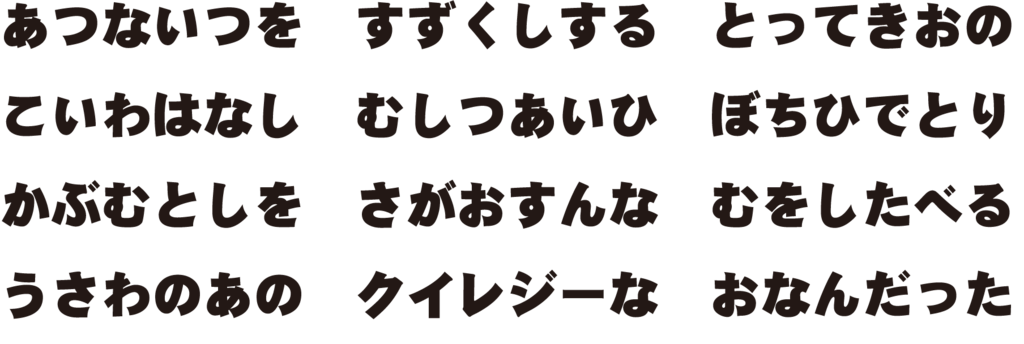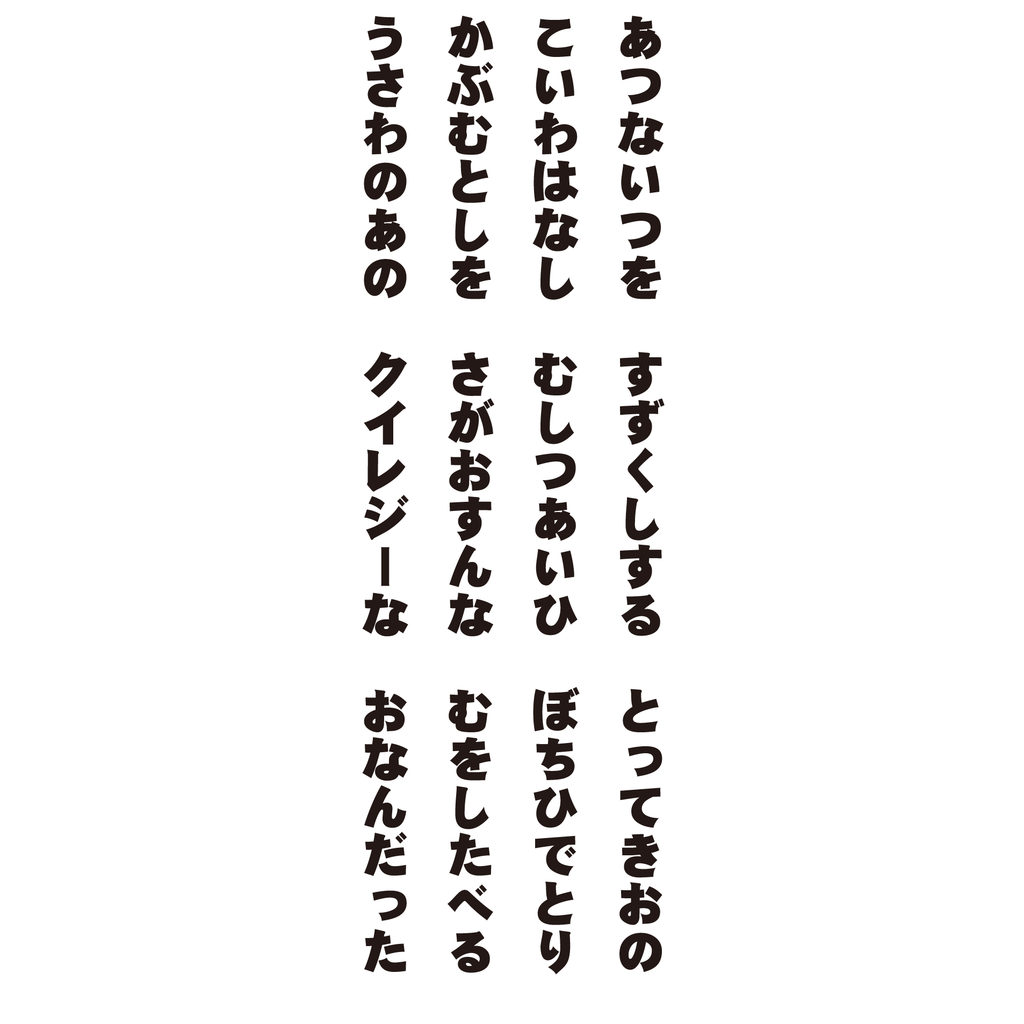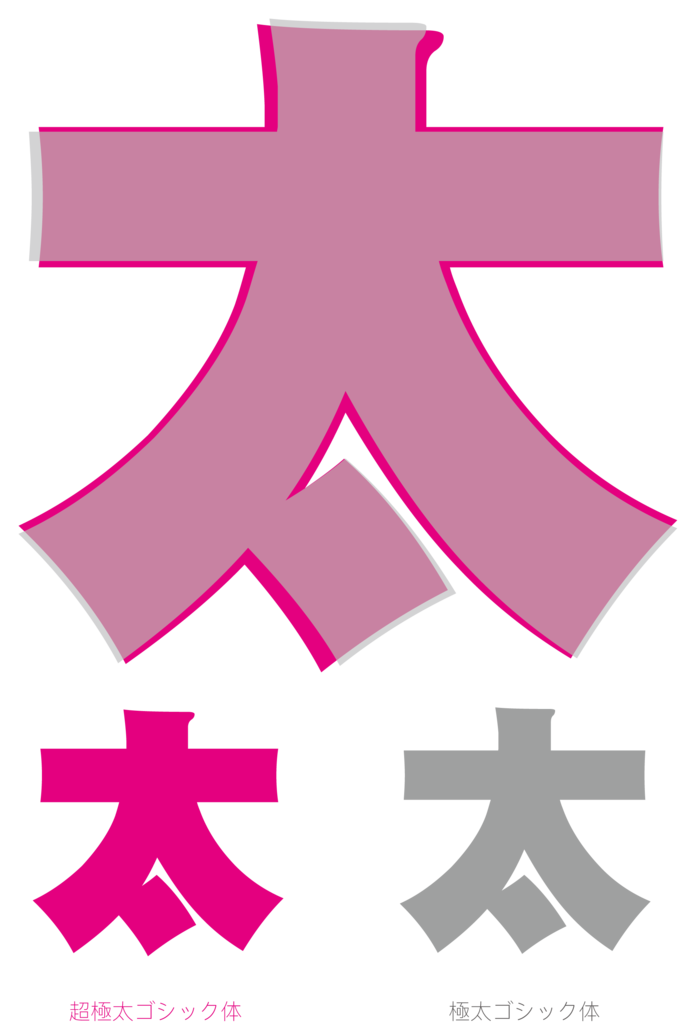
超極太ゴシック体
華康ゴシック体をベースに開発された極太なゴシック体。極太ゴシック体のストロークよりさらに太い超極太な字形の為、より強調したい場面などにオススメ。
超極太ゴシック体と極太ゴシック体の太さを比較
ダイナフォントには極太ゴシック体というフォントもある。そこで超極太ゴシック体と太さを比較してみた。
超極太ゴシック体より少し細い「極太ゴシック体」は、大人気ゲームのスマブラ参戦!!フォントでもおなじみのフォント。